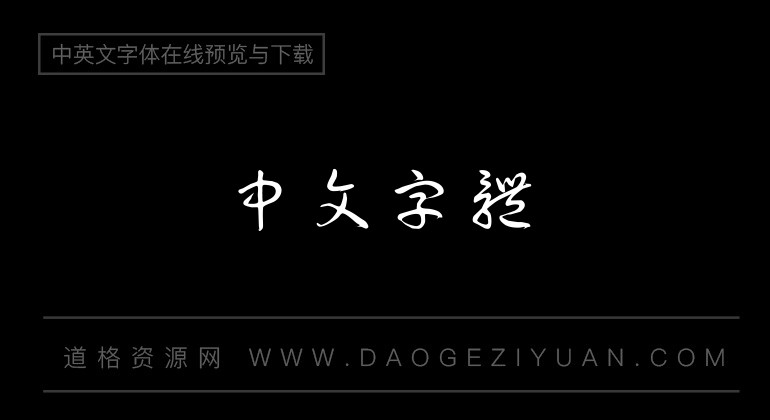
腾祥伯当草书
腾祥伯当草书是一款经典的草书字体,由腾祥伯当先生创作,具有细腻、清新、秀美的风格。它采用自然的线条,比较细腻,笔画清晰,线条细腻,有一种柔和的气息,可以给人一种清新的感觉。它的结构紧凑,拥有较强的穿透力,能够完美地表达出文字的精确性和优雅性。
腾祥伯当草书是一款非常不错的手写艺术字体,具有很好的视觉感,适合于文化类的宣传设计、商业类品牌的广告和产品包装设计以及个性化文字排版等较多场景。